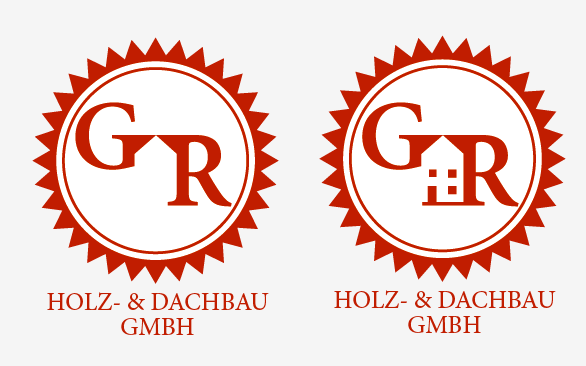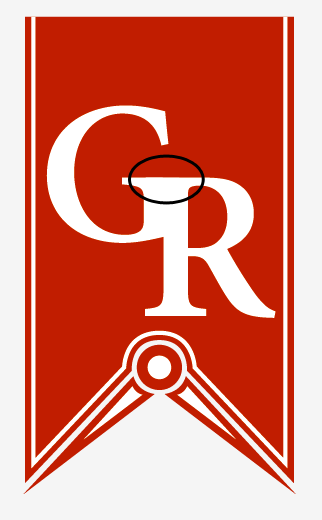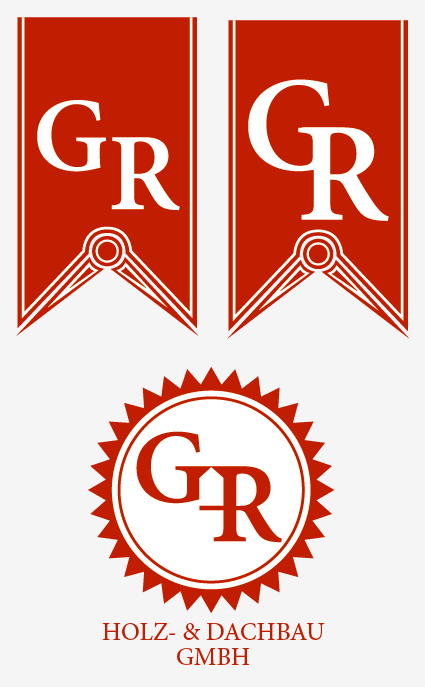
Anregung/Kritik Logo Dachdecker
für einen Dachdecker/Zimmerer soll ich ein neues Logo entwerfen. Mein erster Gedanke war direkt: Es wird ein Logo ohne angedeutetes Dach. Gibt es einen Dachdecker in Deutschland der kein Dach im Logo hat? :?
Nach einigem ausprobieren bin ich bei der Minion hängen geblieben und mit der Wahl auch zufrieden. Möchte einfach mal eure Meinung bzw. Kritik zu den Entwürfen hören.
Ich dachte du wolltest keine Dächer andeuten??
Bie den Fahnen ist der Zirkel (oder was genau das auch sein mag...) schon irgendwie dachig, wobei mir die rechte Fahne besser gefällt.
Im Unteren Logo entsteht zwischen G und R ja auch ein Haus...
Den Brief find ich auch ganz schön, das rot gefällt mir – in der Darstellung auf meinem Monitor... – gut :-)
Das mit dem "dachig" meinte ich so.
So dachig mag ich es nicht. Eher subtiler.
das untere ist nicht schlecht, wenn du aber zwischen G und R ein haus andeuten willst muss da noch was hin z. b. eine tür?
die proportionen zwischen typo und signet sind merkwürdig, das signet sollte viel kleiner werden und die typo vielleicht in bold?
die rechtsform (GmbH) muss doch nicht im logo sein, oder?
Sitze da erst seit heute dran. Das mit der Tür ist ne feine Idee. Hast Recht, die GmbH kann ich aus dem Logo kicken!
Die GmbH würde ich drin lassen, das ist wenigstens so ein winzig kleines bisschen Vertrauensbildung, zeigt es doch von einer gewissen Mindestgröße und Ernsthaftigkeit (ob das dann immer so ist ist wieder was anderes).
Kurz-Rückmeldung:
- Das Monogramm im Entwurf rechts lese ich als CR
- bei den ersten beiden Entwürfen sind mir unten zu viele und damit zu komplexe Linien. Das sind 9(!) Rot-Weiß-Wechsel auf engstem Raum in der Diagonalen, dazu noch mit spitzen Winkeln und dann kommt noch der Kreis dazu mit zusätzlichen Linien. Hat das irgend einen speziellen Grund, oder könnte man es vereinfachen?
- Das mit dem Haus zwischen G und R: könnte man ausbauen, aber wenn das die zentrale Idee sein soll, muss es größer werden ...
Mit dem CR stimmt. Habe es mal etwas geändert. Das mit den Linien hat keinen speziellen Grund. Habe auch das mal reduziert, allerdings finde ich, das es jetzt platter aussieht.
Die untere Idee mit dem Häuschen läuft meiner Meinung nach Gefahr ins Kitschige abzurutschen, oder mir fehlt einfach die zündende Idee.
Das Banner gefällt mir besser, dazu allerdings zwei Anregungen: Den Übergang von G zu R solltest Du überarbeiten, er sollte eher leicht nach Unten geschwungen sein, statt wie jetzt nach Oben gewölbt. Und der Schriftschnitt ist eher was für den ganz kleinen Druck auf ner Geschäftskarte oder nem Kuli oder so; in der Größe wie jetzt die Grafik ist, geschweige denn nem Schild oder Banner, solltest Du nen Displayschnitt mit feineren Serifen verwenden, das ist sonst zu grob...
Ich finde den zweiten Ansatz, mit dem Häuschen im Signet, ziemlich ausbaufähig. Das Haus als Gegenform ist ein cleverer Ansatz. Da solltest du, meiner Meinung nach, dranbleiben.
Ich hab das grad nochmal zwischen Tür und Angel angeschaut und bin prompt drübergestolpert, dass ich "Handwerk" mit "Mensch" verbinde. Bei "Mensch" möchte ich aber einen Namen lesen, damit ich mir die Person dahinter vorstellen kann. Und wenn ich so in mich gehe und mir anschau, wie ich Handwerker im Branchenbuch selektiere – wenn ich denn mal einen brauch – dann erinnere ich mich dass ich immer die zuerst anruf, die einen Namen angeben. Eine "GR GmbH" oder "G+R GmbH" würde ich nicht kontaktieren, das ist mir für einen Handwerker zu unpersönlich. Ich denke das sollte in eine Logofindung mit einbezogen werden.
er sollte eher leicht nach Unten geschwungen sein, statt wie jetzt nach Oben gewölbt.
Da stehe ich gerade aufm Schlauch wie du das meinst!
Danke allen für die Anregungen!
Schau, hier wölbt sich was nach oben:
Und hier nach unten, hab ich allerdings nur im Photoshop schlampig übermalt, und bewusst stark übertrieben, damit man's erkennt. An den Pfaden solltest Du natürlich auch nur so viel verändern, dass die Wölbung so sanft ist wie bei Beispiel 1 - nur eben in die Gegenrichtung :D
Ah, ok. Jetzt hab ichs verstanden. Die Wölbung ist nur da, weil es ein schneller Entwurf ist. Ist ja noch keine Reinzeihnung. Ist aber eine gute Idee von dir.
Ich würde einmal das G und das R so setzen das die Grundstricke sich nicht sumieren sonder überlagern, da entsteht etwas ein Klumpen bei dir, was zwar in diesem Falle nicht so stört, aber versuch es mal so in der Art:
ach ja CR ok, hab Threat noch mal überflogen und gefunden :cheer:
Bei der Schriftauswahl solltest Du darauf achten, dass man der Schrift nicht ansieht, dass sie eine Textschrift ist. Sie sollte interessante Details haben, die gut zur Strichstärke der anderen Logoelemente passen.
Das zweite Logo würde ich in der Forma fallenlassen. Der Kranz ist sehr austauschbar. Die Idee ist nicht schlecht, aber Du solltest dann nicht an einer Schrift herumoperieren, sondern vielleicht die zwei Buchstaben selbst basteln.